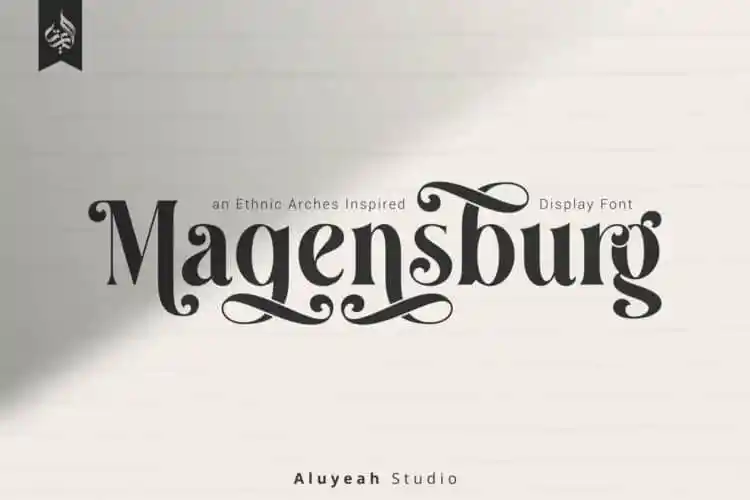
Magensburg Serif Font – Download Grátis
Magensburg Serif é uma fonte serif vintage projetada cuidadosamente por Aluyeah Studio. Ela foi criada para oferecer um apelo ligeiramente femenino, com um espaçamento bastante estreito que deixa o texto muito próximo uns dos outros. Esta font não é apenas uma versão tradicional da família de letras serif; ela também inspirou elementos arquitetônicos orientais em sua criação. Com seu design meticulosamente cuidado e influência nas arcadas asiáticas, Magensburg Serif oferece um olhar de luxo e misterio ao design. Este é um recurso que combina elegância com sofisticação, criando uma atmosfera encantadora nos projetos gráficos onde é aplicada. Pode-se usar a Magensburg Serif para dar mais profundidade e beleza aos textos em sites, impressões digitais e qualquer outro tipo de design visual que você possa imaginar. Adicionar um pouco de magia ao seu próximo projeto com Magensburg Serif, uma fonte serif cuidadosamente elaborada. Seja na linha da frente ou no fundo do pântano, esta font tem a capacidade de tornar sua mensagem mais forte e envolvente.